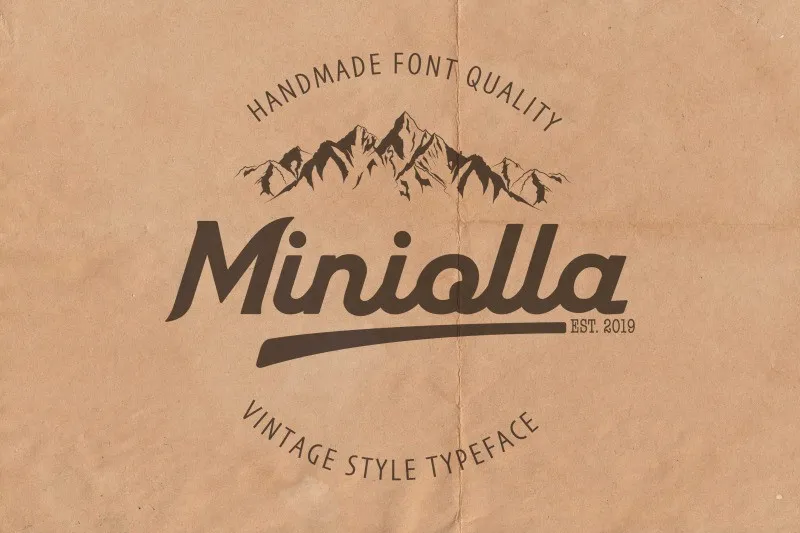
Miniolla é uma fonte escrita à mão que se destaca por sua elegância e audacia. Perfeita para dar um toque estiloso a seus projetos de headlines e logotipos, Miniolla apresenta uma aparição moderna com estilo vintage, mantendo-se fiel ao formato de 70 anos sem perder o seu caráter único. A fonte traz consigo a característica maravilhosa dos esquifes nas letras finas, adicionando um toque diferenciado e revigorante à sua tipografia. Seja você designer ou grafista, Miniolla é uma ótima escolha para adicionar um ar de sofisticação e personalidade a qualquer projeto visual em seu portfólio. A fonte, criada por 99designs, oferece a opção perfeita de estilização para aqueles que desejam dar novos rumos aos seus projetos gráficos com um estilo audaz.